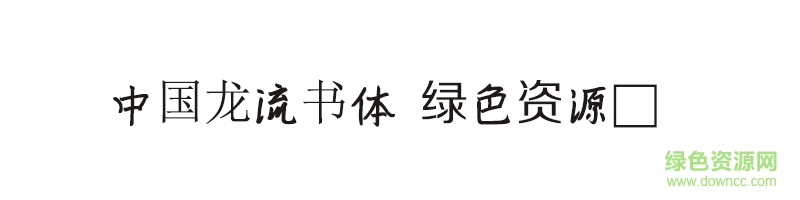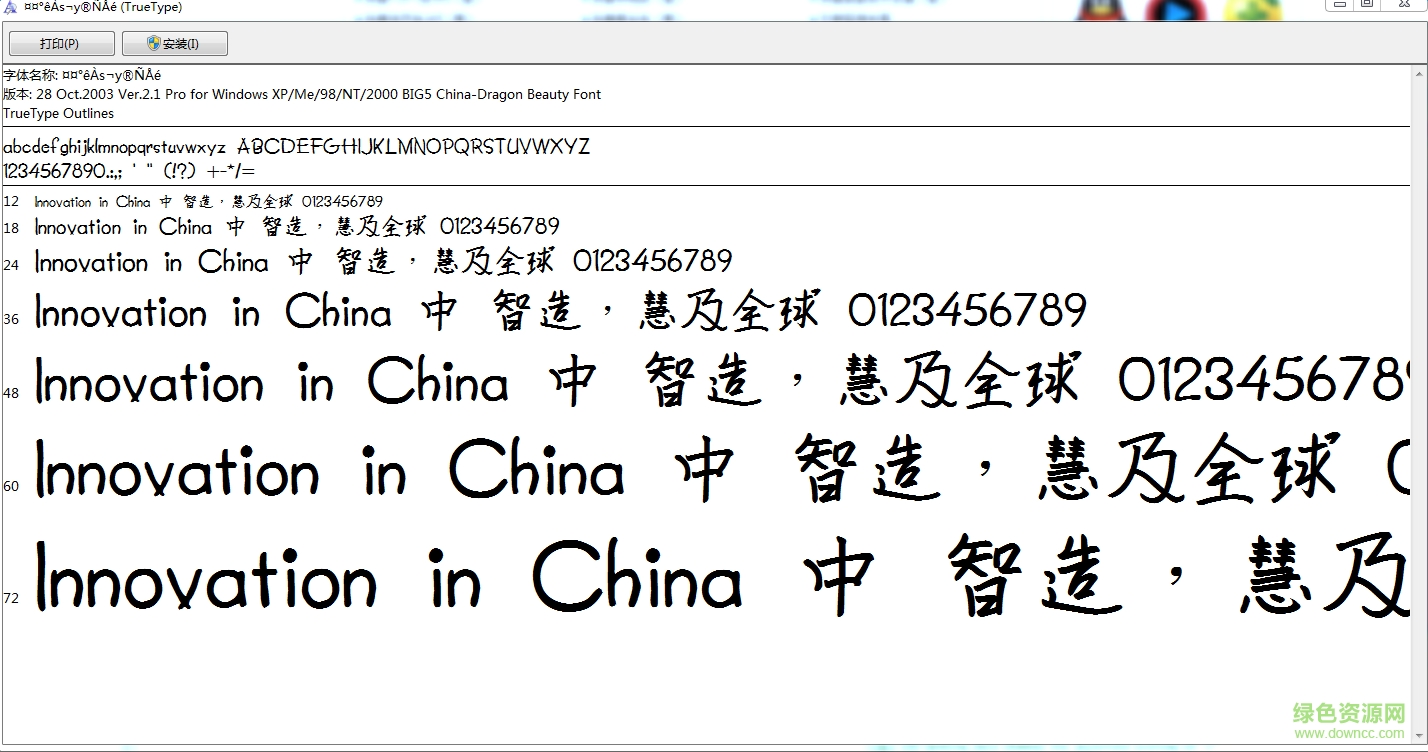
中國(guó)龍流書體字體是一款中國(guó)風(fēng)流書類字體軟件,字體形如流水,給人一種整體舒服的感覺(jué),適合各種批閱書法,非常耐看,喜歡的朋友歡迎來(lái)綠色資源網(wǎng)下載體驗(yàn)!
在藝術(shù)設(shè)計(jì)和各種商業(yè)海報(bào)的制作中,字體的風(fēng)格選擇是十分重要的,不同的風(fēng)格字體都會(huì)造就不同的視覺(jué)效果。而中國(guó)龍流書體字體是一套充滿中國(guó)風(fēng)的中文字庫(kù),綠色資源網(wǎng)給大家提供好看的中國(guó)龍流書體字體!